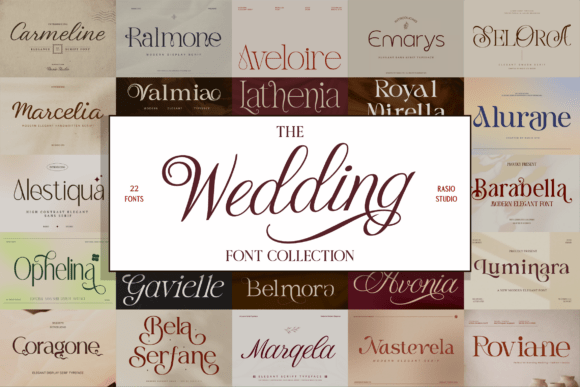
Wedding Collection
์˜ฌ๋ฐ”๋ฅธ ๋””์ž์ธ ์š”์†Œ๋ฅผ ์ฐพ๋Š” ๊ฒƒ์€ ์–ด๋ ค์šธ ์ˆ˜ ์žˆ์ง€๋งŒ Wedding Collection๋Š” ์ž‘์—…์„ ์ฆ‰์‹œ ํ–ฅ์ƒ์‹œํ‚ค๋Š” ๋›ฐ์–ด๋‚œ ์ปฌ๋ ‰์…˜์„ ์ œ๊ณตํ•ฉ๋‹ˆ๋‹ค.
์ •๋ฐ€ํ•˜๊ฒŒ ์ œ์ž‘๋œ Wedding Collection๋Š” ๊น”๋”ํ•œ ๋ฒกํ„ฐ, ๋ถ€๋“œ๋Ÿฌ์šด ํƒ€์ดํฌ๊ทธ๋ž˜ํ”ผ ๋ฐ ์•ˆ์‹ฌํ•  ์ˆ˜ ์žˆ๋Š” ์ƒ์—…์šฉ ๋ผ์ด์„ ์Šค๋ฅผ ์ œ๊ณตํ•ฉ๋‹ˆ๋‹ค.
POD(์ฃผ๋ฌธํ˜• ์ธ์‡„) ์ œํ’ˆ, ๊ฒฐํ˜ผ์‹ ์ดˆ๋Œ€์žฅ ๋˜๋Š” ์†Œ์…œ ๋ฏธ๋””์–ด ๊ทธ๋ž˜ํ”ฝ์„ ๋งŒ๋“ค ๋•Œ Wedding Collection๋Š” ์ด์ƒ์ ์ธ ์„ ํƒ์ž…๋‹ˆ๋‹ค.